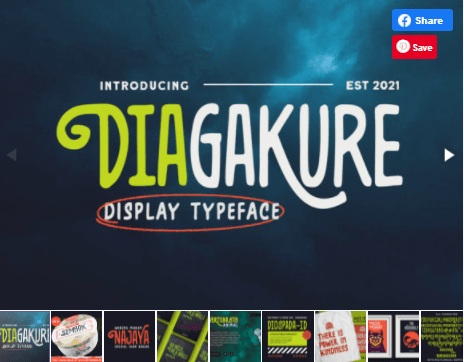
Diagakure Font
Diagakure - это крутой, адаптируемый дисплейный шрифт в винтажном стиле. Он закодирован в кодировке PUA, что означает, что вы можете легко получить доступ ко всем глифам и росчеркам!
Влюбитесь в его невероятно универсальный стиль и используйте его для создания эффектных дизайнов!
Diagakure - это крутой, адаптируемый дисплейный шрифт в винтажном стиле. Он закодирован в кодировке PUA, что означает, что вы можете легко получить доступ ко всем глифам и росчеркам!
Влюбитесь в его невероятно универсальный стиль и используйте его для создания эффектных дизайнов!